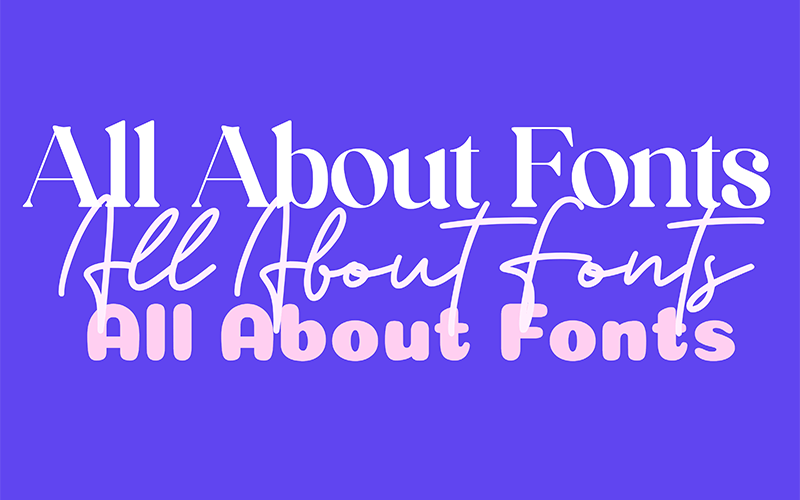
Come scegliere i migliori loghi per font per il tuo design
Il design del logo è una corsa sfrenata per ogni proprietario di un marchio, quindi quando diciamo che scegliere il carattere giusto è abbastanza importante, fidati di noi! Non solo sul tuo logo, però, la scelta del tuo carattere gioca un ruolo enorme nel tuo processo di branding. Non sottovalutare i caratteri! Quindi non diciamo altro e tuffati subito in tutto ciò che devi sapere sui loghi dei caratteri .
Per scegliere il miglior font per i loghi , devi considerare il tuo pubblico, lo stile del tuo marchio e quando e dove guarderanno il design del tuo logo. Immergiamoci subito!
Come scegliere il carattere ideale?
Come detto prima, ci sono alcune cose da considerare prima di scegliere un font solo perché ti dà le vibrazioni giuste. Esaminiamo alcuni:
- Il miglior carattere per un logo è quello che è leggibile in tutte le dimensioni, grandi o piccole.
- Fai la ricerca di un concorrente perché non vuoi che il tuo logo assomigli alla concorrenza.
- Rifletti l'identità del tuo marchio, qualcosa che rifletta il tuo stile.
- Evita di utilizzare più caratteri sul tuo logo, mantienilo il più semplice possibile.
- Evita di usare caratteri alla moda. Ciò che è popolare oggi potrebbe non esserlo domani. Non scegliere un carattere in base alle tendenze della moda.
Qual è il carattere migliore per i loghi?
Ci sono un sacco di diversi tipi di carattere tra cui puoi scegliere: serif, sans serif, corsivo, scrittura a mano e altro ancora. Diamo un'occhiata a ciascuno di questi per aiutarti a decidere.
Che cos'è un carattere Sans Serif?
Un serif è un trattino alla fine della riga di una lettera. Un font serif sans (francese per senza) è qualsiasi font che non ha quei piccoli trattini alle estremità come fa Time New Roman o, in pratica, tutti i font serif.
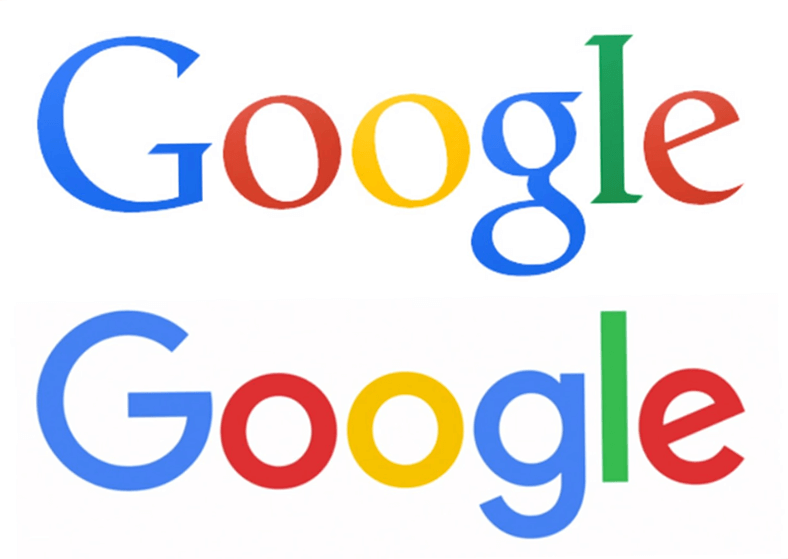
I caratteri sans serif sono anche conosciuti come le tipografie moderne per i caratteri del logo moderno. I caratteri sans serif più conosciuti sono Arial, Helvetica, Proxima Nova, Futura, Calibri, Helvetica Now, Proxima Nova, Franklin Gothic, Myriad, ItalicTT Norms Pro e Avenir Next , tra gli altri.
I migliori caratteri Sans Serif
I caratteri sans serif sono i caratteri più comuni e versatili da utilizzare nei progetti di branding. Sono chiari, leggibili e semplici. Poiché sono così versatili, funzionano straordinariamente bene per tutti i tipi di industrie. Se vuoi un'immagine giovane e accessibile, questo tipo di carattere è sicuramente la strada da percorrere. Riuscirai a far sembrare il tuo logo più accessibile e giocoso!
Alcuni dei migliori font Sans Serif da utilizzare sui design del tuo logo sono:
Helvetica ora
Prossima Nova
Futura
Marmellata grottesca
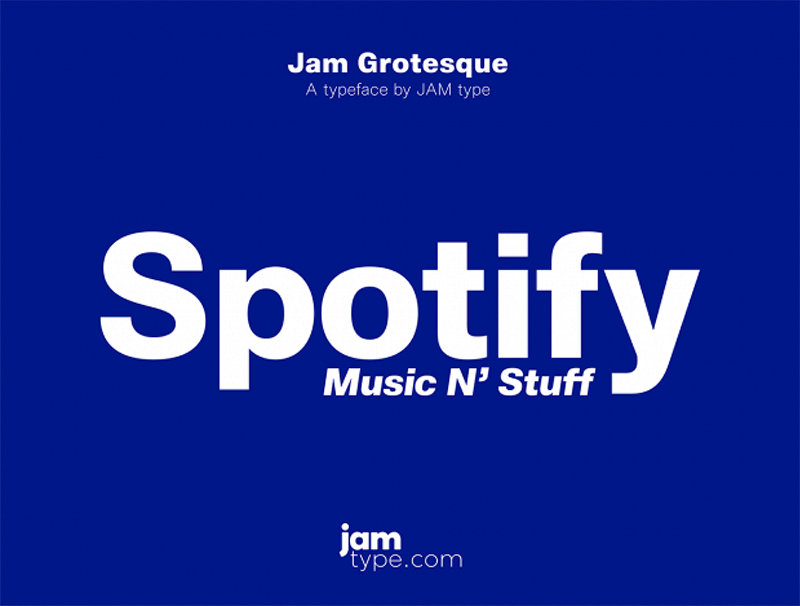
Geonik Pro
E altri come: BR Cobane, Open Sans, Qualy, Vilane, Code Next Monaco, Spacia, Bequest, hai l'idea che la lista sia ampia.
I migliori caratteri Serif
Se vuoi optare per un modo più classico, i caratteri Serif sono sicuramente la strada da percorrere. I caratteri Serif appaiono formali e sofisticati. Sono un'ottima scelta per i settori tradizionali come studi legali, società finanziarie e altro ancora.
Alcuni dei caratteri Serif più popolari sono Times New Roman, Trajan, Baskerville e Georgia Italic, tra gli altri.
I migliori caratteri corsivi
La scrittura corsiva è uno stile più classico per il tuo logo poiché esiste da secoli ormai. Questi sono belli e piacevoli da vedere, quasi disegnati a mano. È un modo sottile per aggiungere un tocco umano al tuo logo.
Tieni presente che i caratteri corsivi possono essere pericolosi se usati su parole lunghe o su piccole scale, possono essere difficili da leggere.
Alcuni dei caratteri corsivi più popolari per i loghi quest'anno sono:
Broadley
Monarda
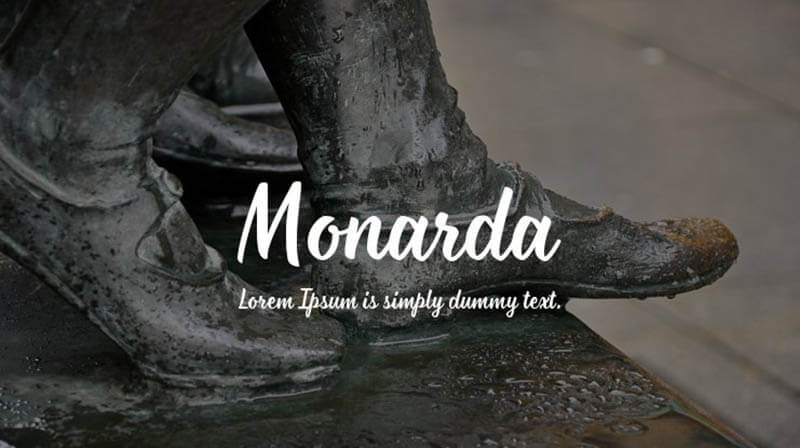
Lago Palmer
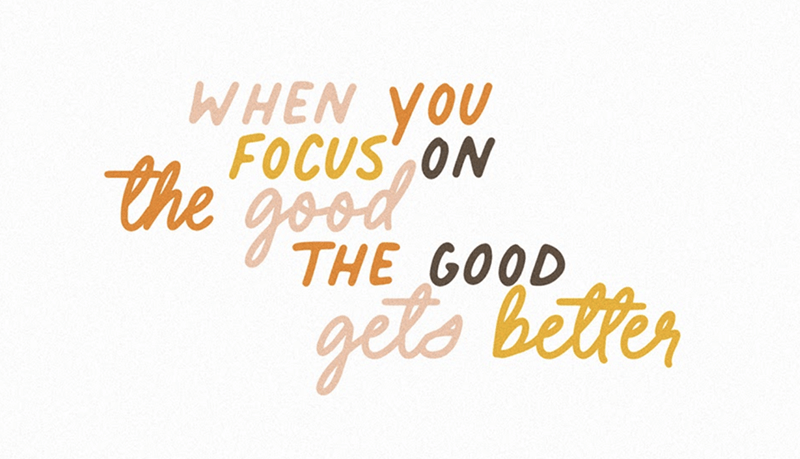
Raksana
Burro di latte
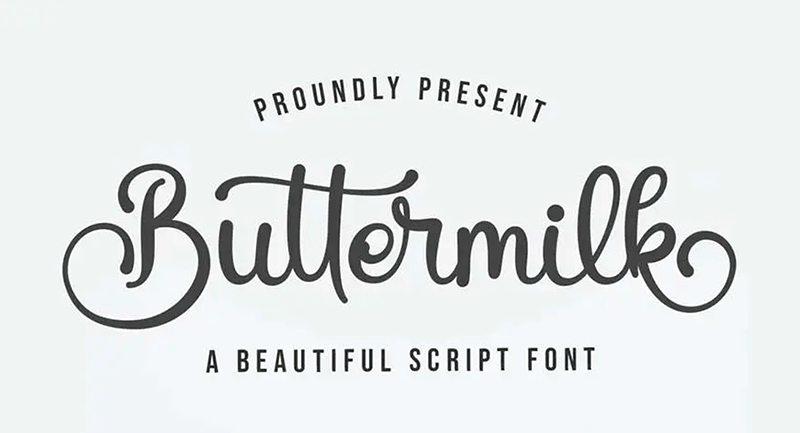
E altri come: Hope Sans, Caratteri corsivi scritti a mano, Krysttal Spears, Aesthetic Notes, Tahu, Billie Sights, Bilanthy, Diary Angelique, Stampa e molti altri. Puoi persino utilizzare alcuni dei migliori caratteri corsivi gratuiti come Flanella, Debby, Variane, Beattingvile, Puzzled, Milkshake, Vegan Style e altri.
I migliori caratteri di script
I caratteri degli script hanno tutti uno stile scritto a mano, come se fossero scritti con una penna che riflette eleganza, creatività e un pizzico di tocco umano. Sono progettati per rispecchiare la scrittura naturale.
Potresti pensare ora, non è lo stesso dei caratteri corsivi? La risposta è no. La principale differenza tra i caratteri di script e il corsivo è che le lettere di script sono tutte collegate tra loro, mentre i caratteri corsivi non devono necessariamente esserlo.
Alcuni caratteri di script popolari sono:
Sceneggiatura Bickham
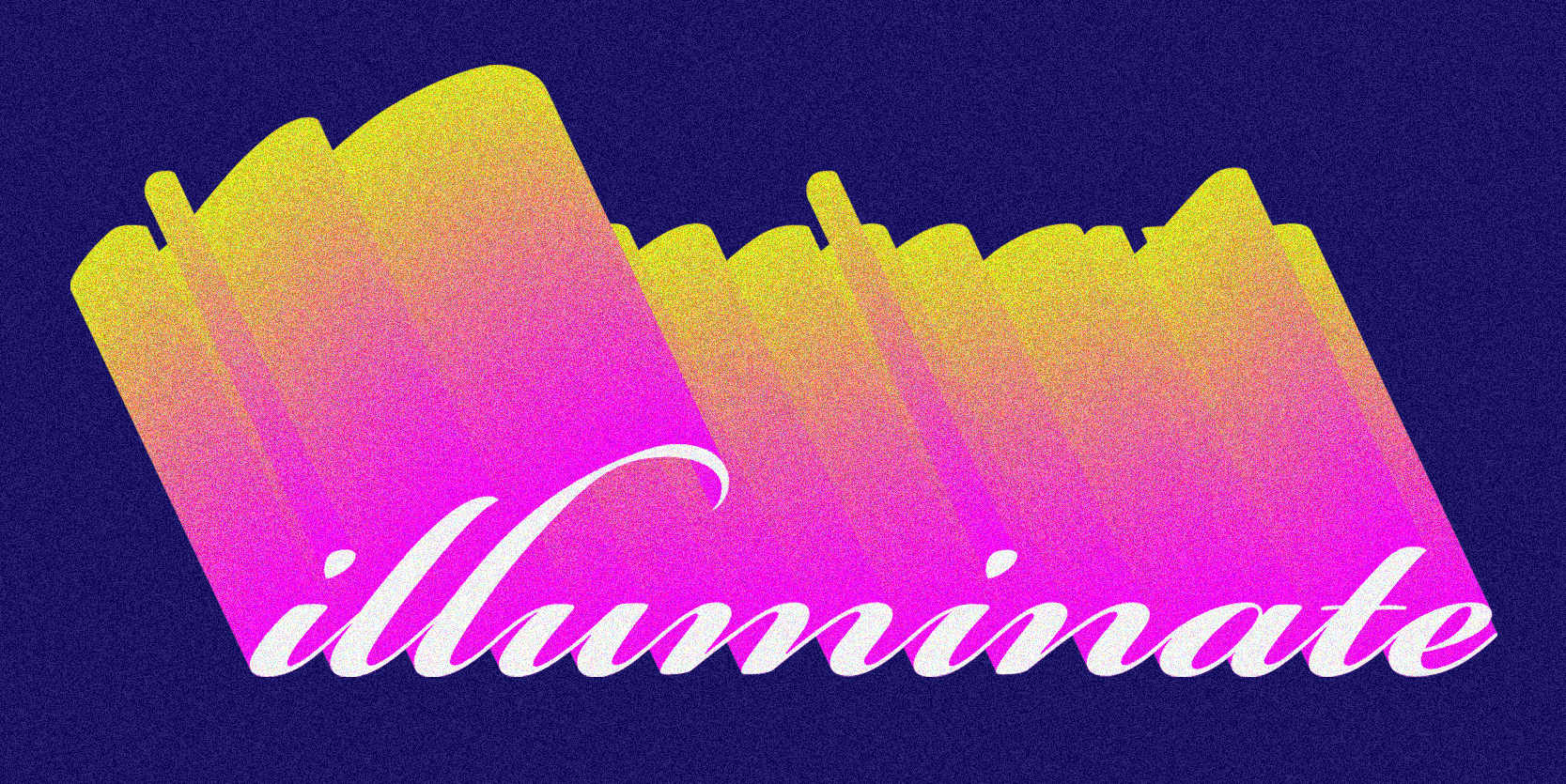
Stampa
Monoline Rampage
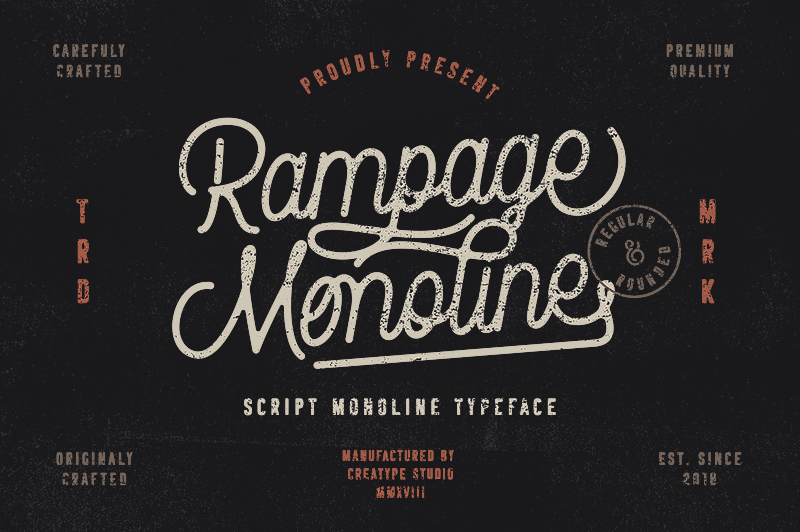
E non dimenticare i migliori font di script gratuiti da scaricare:
Scrittura edoardiana
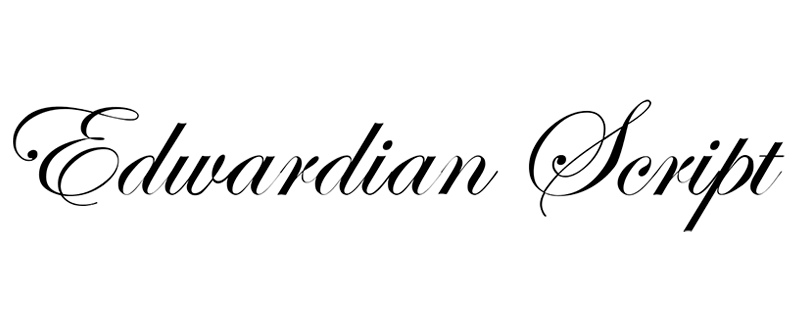
Lavanderia
Alessio Pennello
Come faccio a creare un carattere del logo?
Bene, si spera che tu abbia già scelto uno stile per il logo del tuo carattere. Quindi ora stiamo andando passo dopo passo alla creazione del tuo logo personale.
- Entra nel creatore di logo di Placeit .
- Digiterai il nome del tuo marchio nella casella di testo.
- Quindi selezionerai il tuo settore
- Scegli un modello di logo che si sposa al meglio con lo stile che stai cercando, non preoccuparti troppo dei dettagli potrai personalizzarlo completamente!
- Adesso arriva la parte divertente! Una volta che sei nella schermata di modifica di un modello di logo, troverai le caselle del tipo nella schermata di sinistra.
6. Puoi scegliere tra i caratteri "recenti", "salvati o "suggeriti", ma se ti senti più creativo, fai clic su "più caratteri" su una di queste opzioni e otterrai la nostra libreria di caratteri.
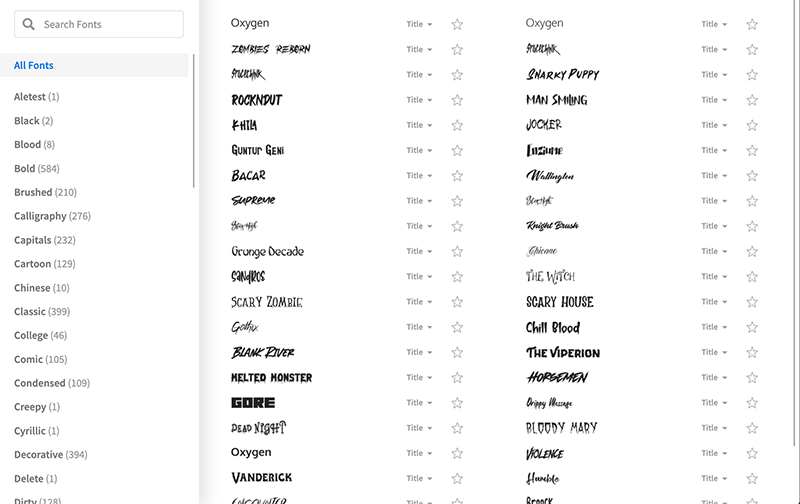
Troverai migliaia di caratteri da provare sul design del tuo logo! Puoi filtrare usando quei tag alla tua sinistra e puoi salvare tutti i caratteri che ti piacciono semplicemente facendo clic sulla piccola icona di inizio.
7. Et voilà! Hai scelto il tuo carattere, il fulcro del design del tuo logo e un elemento importante per tutto il materiale del tuo marchio.
Puoi anche provare questa tela bianca per ricominciare da capo!
Che cos'è un logo basato sui caratteri?
Abbiamo tutti in mente un logo basato sui caratteri. Raggiungere il massimo della mente su un logo ha molto a che fare con la scelta del carattere giusto, o anche insolito! Esprimi lo stile del tuo marchio solo con caratteri e colori.
🔥 Scopri di più su tutti i tipi di loghi esistenti e scopri il meglio per te rispondendo a questo veloce quiz!
Quali caratteri possono essere utilizzati gratuitamente in un logo?
Quando usi questo strumento per la creazione di loghi, ottieni una vasta selezione di caratteri tra cui scegliere. Tuttavia, puoi provare alcuni loghi gratuiti e puoi provare questi modelli senza spendere un solo centesimo!
Ultimo, ma non per importanza
Creare il tuo logo design non è un picnic, ci sono tonnellate di decisioni importanti da prendere che daranno forma al tuo marchio per esprimere ciò che riguarda la tua attività. Scegliere di creare un logo font è sempre un'ottima idea. Ci sono un sacco di fantastici font per i loghi , ma consideri ciò che ognuno di loro dirà del tuo marchio.
Per scegliere il font perfetto per il tuo logo, considera sempre chi è il tuo pubblico, che aspetto ha la tua concorrenza e quando e dove le persone guarderanno il tuo logo!